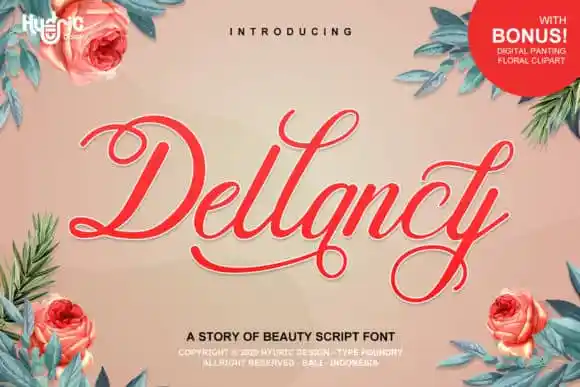
Dellancy Script Font – Download Grátis
A Dellancy Script Font é uma elegante fonte escrita a mão seguindo a tipografia puro estilo calligrafia. Com todas as figuras e desenhos complementares codificadas com PUA (Prefered User Access), torna o processo de uso muito mais conveniente. Esta fonte criada pelo designer HydricDesign é perfeita para aqueles que querem adicionar um toque único a seus projetos digitais, seja em e-mail marketing, logotipos, design gráfico ou até mesmo em criações de artes digitais. A Dellancy Script Font traz à vida uma versão autêntica da escrita humana em formatos sofisticados e profundos, tornando-a a escolha perfeita para quem valoriza o encanto do desenho a mão no digital.